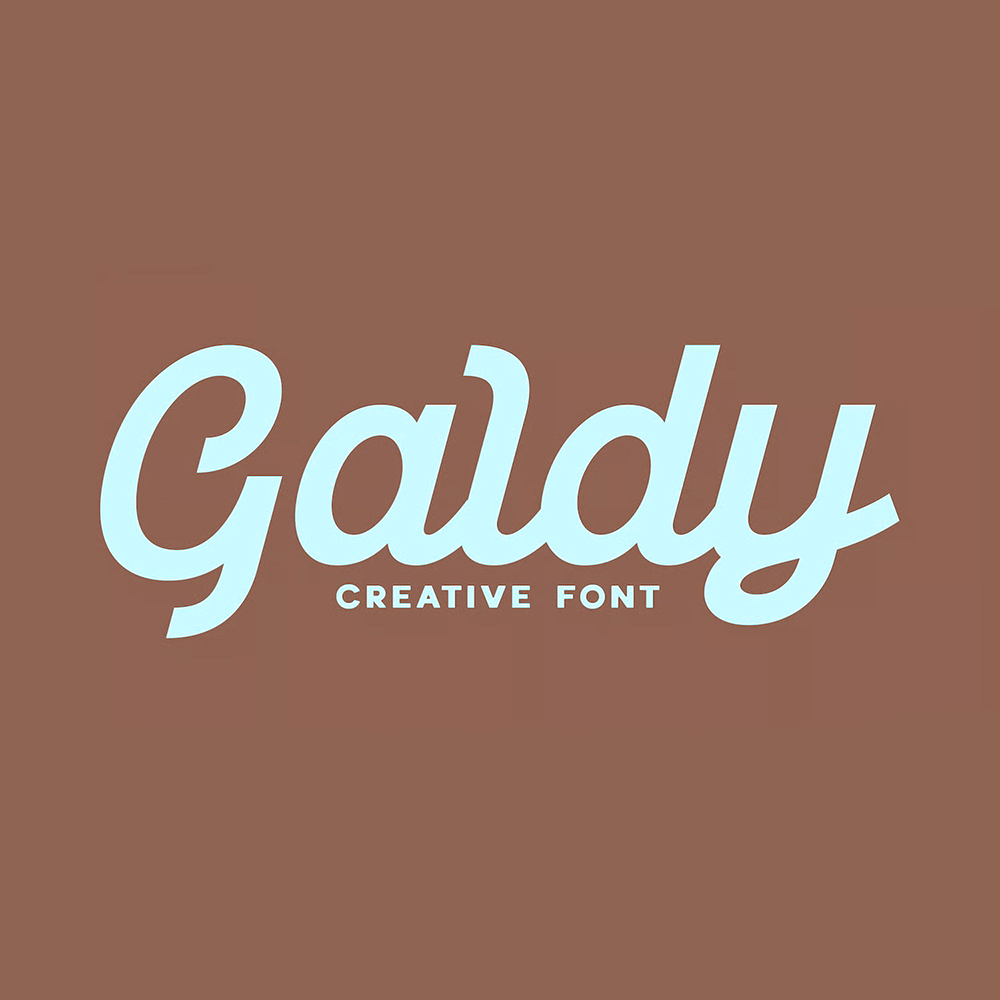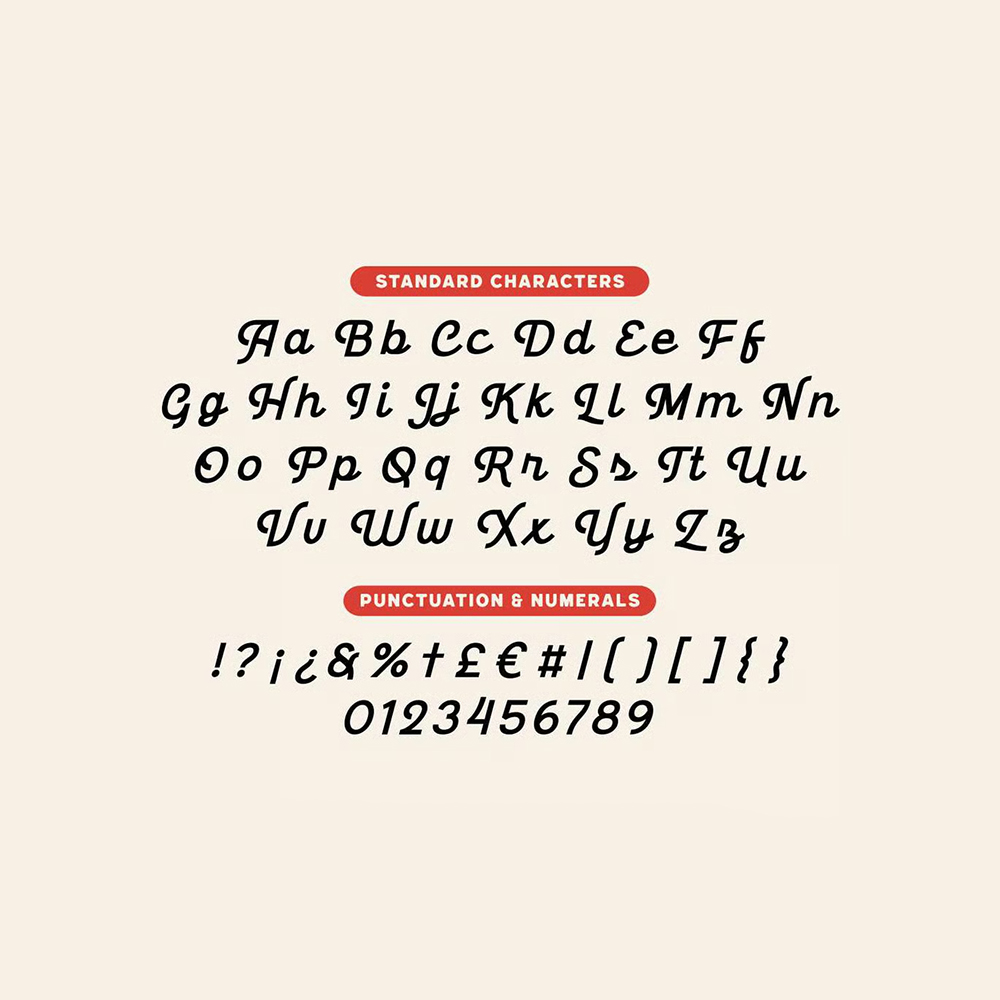
فونت پرمیوم و انگلیسی Galdy فونت اسکریپتی با ظاهر و حس قدیمی هست که از طراحی حروف دهه ۱۹۸۰ الهام گرفته شده و برای پروژههای امروزی که ظاهری قدیمیتر دارند، قویتر و جسورانهتر شده. هدف، استفاده از طرحهای ساده اما مؤثر از این دوران بود. فونت گالدی برای لوگوی محصول، پوستر، تیتر، لوگوی کارت، لوگوی برند لباس، آثار هنری حروفنگاری، طرحهای تیشرت، طراحی قدیمی، مجله، بستهبندی، لوازم التحریر و موارد دیگر عالی است. به راحتی میتوانید با این فونت تایپ لوگوی خود را ایجاد کنید. گالدی دارای ویژگی Open Type است که به شما امکان دسترسی به مجموعه بزرگی از حروف جایگزین منحصر به فرد و بسیاری از لیگاتورها را میدهد تا ایجاد آن را برای شما آسانتر کند.